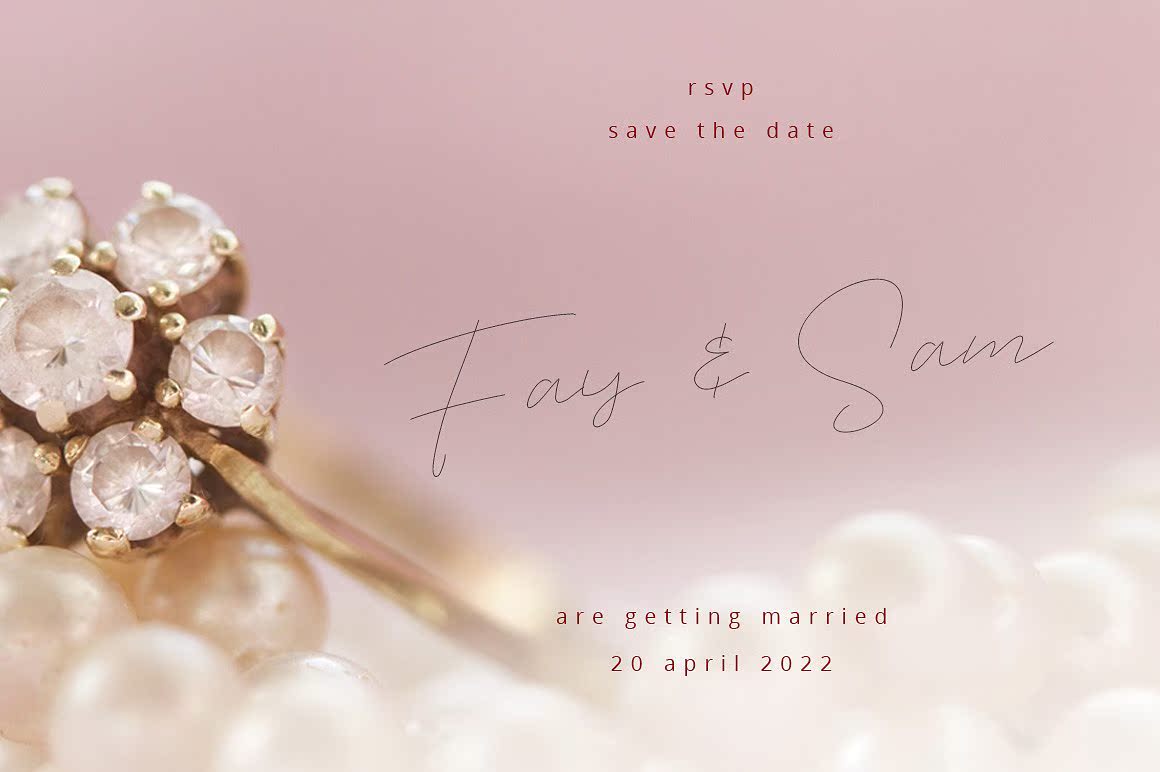
JETSEATSCRIPTISOUR产品具有丰富的文字和书写风格。我们是设计师,并能为您提供最好的服务。这非常适合于发布日志、邀请、海报、杂志、,照片和其他设计项目。JETSEATSCRIPTISOUR产品具有丰富的文字和书写风格。我们的设计和制作最适合您。这非常适合于日志、邀请、海报、杂志、照片和其他设计项目。